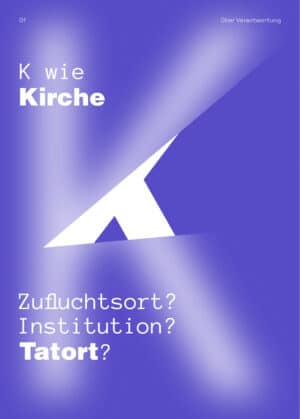
Der Type Directors Club New York hat erneut die beste Gestaltung weltweit auszeichnet. Wir stellen in fünf Teilen unsere Favoriten vor. Heute: Editorial Design – und das reicht von Handarbeit zu Augmented Reality.
Im vierten Teil unseres Best-of des Type Director Clubs New York 2022, des hochkarätigen, weltweiten Wettbewerbs, zeigen wir eine kleine Auswahl an Editorial Design, das ausgezeichnet wurde.
Wie schon die großartigen getöpferten Poster in der Kategorie Plakatdesign, stammen gleich vier der spannendsten Gewinnerprojekte im Editorial Design aus der Nachwuchs-Kategorie Young Ones TDC – und eines davon erneut von der Hochschule für Gestaltung Offenbach.
In die Zukunft blättern
Dort hat Verena Mack ihre Illustrationen »Nonbinary Future« in einem Magazin zusammengefügt und in Reise verwandelt, die vom binären in das nonbinäre Spektrum führt.
Werden am Anfang des Magazins NON/BINÄR Sexismus, Queer-Feindlichkeit oder Hierarchien des binären Systems kritisiert, geht es mit jedem Umblättern weiter in eine Welt, in der das drängende Bestreben nach Akzeptanz herrscht, das Auflösen von Rollenbildern und Machstrukturen und den Weg für die Utopie ebnen, die den Abschluss des Magazins bildet.
Und auch die Gestaltung nimmt diese Entwicklung auf. »Das Magazin wird von der binären Doppelseite durch Ausklappseiten in ein größeres Format erweitert«, beschreibt Verena Mack ihr Konzept. »Auf den letzten Seiten beginnt das Magazin sich durch Konturschnitte aufzulösen, wobei durch das Umblättern neue Bildkombinationen entstehen, welche das Verwischen von Grenzen und den Austausch untereinander visualisieren.«
Editorial Design als Sternmarsch
Mit der Schönheit des Miteinanders beschäftigt sich auch die wunderbare und verblüffende Publikation Freund*innenschaft von Julia Klenovsky .
Bereits auf die Shortlist des Förderpreises für junge Buchgestaltung 2021 der Stiftung Buchkunst gesetzt, feierte jetzt auch der TDC die Abschlussarbeit der Studentin der Hochschule Augsburg.
Deren Editorial Design folgt dem Prinzip eines Sternmarsches bei dem sich Menschen aus verschiedenen Richtungen auf ein gemeinsames Ziel zubewegen. In diesem Fall ist es das Buch von Julia Klenovsky, das dem von Frauen geprägten Freundschaftsbegriff folgt – und dabei nichtbinäre Personen ebenso einbezieht wie alle anderen, die sich als Frau identifizieren.
Werden im Zentrum der Freund*innenschaft verschiedene Stimmen und Standpunkte zusammengebracht, folgen auch Typografie und Illustration diesem Prinzip.
Gleichzeitig ermutigt ein flexibler Buchrücken dazu, die beiden Buchdeckel zusammenzuführen und die Hierarchie von Anfang und Ende aufzuheben.
Ein Leineneinband und ein Schuber hingegen schützen die Geschichten von 17 Autorinnen deren Illustrationen gestalterisch an mittelalterliche Darstellungen angelehnt sind, der Zeit von Unterdrückung und Hexenverfolgungen, die aber im Gegensatz dazu von Freundschaft und Solidarität erzählen.
»Dieses Buch exponiert und zelebriert, es träumt und trauert«, sagt die Illustratorin, Grafikdesignerin und Künstlerin über ihren inhaltlichen und visuellen Sternenzug. »Freund*innenschaft ist ein konzeptionelles Buch, das Raum für die Beziehungen zwischen Frauen* schafft.«
Wenn Buchseiten laufen lernen
Schön öfter haben wir über die Arbeit der Berliner Agentur Neue Gestaltung berichtet, vor deren umwerfenden Publikationen wie Vertauschte Köpfe und allem auch von ihrem Umgang mit Augmented Reality.
Ihre Gestaltung für das Theater Erlangen wurde bereits ausgezeichnet, allen voran ihre Plakate, deren Motive mit Hilfe der Theater-Erlangen-App plötzlich in Bewegung geraten.
Genauso wie im Spielzeitheft, das in diesem Jahr ebenfalls beim TDC ausgezeichnet wurde:
Bild: Neue Gestaltung
Aufregend autobiografisches Design
Die Arbeiten des chinesischen Gestalters Yiwei Dai, der an der Tongji University in Shanghai studiert, sind sehr persönlich.
In seinem Buch I’m Proud Of You, das ebenfalls bei den Nachwuchsprojekten Young Ones des TDC ausgezeichnet wurde, erzählt von seiner Erziehung.
Auf dem Cover: die Beyblade mit der seine Mutter ihn schlug, innen eine Reise ins Erwachsensein unter den unterschiedlichen Einflüssen und mit den verschiedensten Gegenständen – und einem Porträt am Rand der Seiten, das ihn wie in einem Daumenkino immer älter werden lässt und seine Entwicklung visualisiert.
Für die Publikation China Shoe Problem hingegen kehrte Yiwei Dai in seine Heimatstadt zurück, die seinen Angaben nach einst das Zentrum chinesischer Schuhherstellung war und erforscht, wie diese unter der Pandemie und den Lockdowns gelitten hat.
Eingearbeitet in das Buch sind die dünnen Papiere, mit denen die Schuhe eingepackt werden und die Yiwei Dai vor Ort gesammelt hat. Die Interviews der Arbeiter mit denen er sprach hingegen, hat er hinter ihren Porträts verborgen um zu visualisieren, da diese keine eigene Stimme haben dürfen.